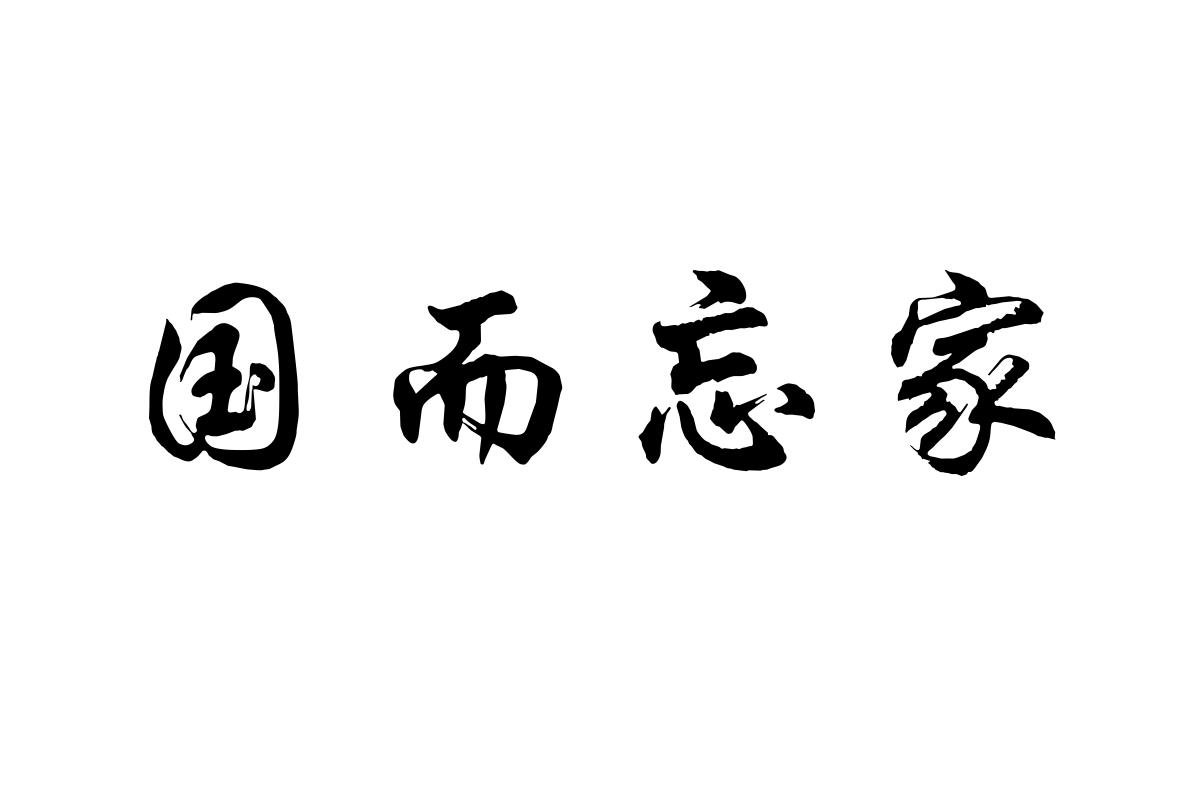
汉仪行楷简是一种基于传统书法风格的现代字体,旨在为用户提供一种既具有传统韵味又不失现代感的字体体验。这种字体的设计灵感来源于古代行书和楷书的精髓,通过精心的字形结构和笔画处理,使得字体既有书法的灵动性,又有现代字体的清晰易读。
汉仪行楷简的特点如下:
1. 字形结构:汉仪行楷简采用传统的行书和楷书结构,保持了汉字的基本形态和结构特点,使得字体既有书法的美感,又不失现代字体的简洁。
2. 笔画处理:汉仪行楷简在笔画的处理上,既保留了传统书法的流畅性和连贯性,又注重笔画的清晰和易读性。这使得字体在视觉上既美观又实用。
3. 风格特点:汉仪行楷简融合了传统书法和现代设计元素,既有古典的韵味,又有现代的气息。这使得字体既适合用于传统的书法作品,也适合用于现代的平面设计和广告宣传等场景。
4. 应用场景:汉仪行楷简适用于各类需要书写或设计的场合,如书籍、报纸、杂志、广告、海报、网页等。它既可以作为个人签名使用,也可以作为商业用途的商标或标识。
总之,汉仪行楷简是一种集传统与现代于一体的字体,旨在为用户提供一种既具有艺术价值又实用的字体选择。